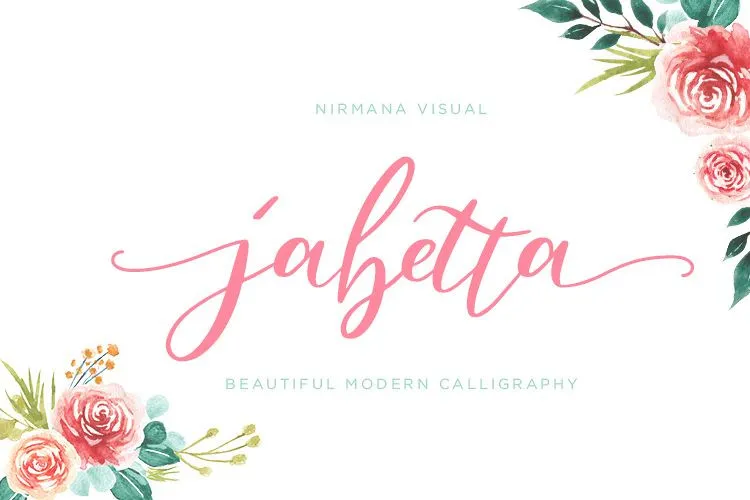
Jabetta Script Font – Download Grátis
A Jabetta Script Font é uma elegante tipografia moderna inspirada na calligrafia. Este tipo de texto possui características únicas que a tornam perfeita para diferentes necessidades de design, especialmente ideal para criações de marca e projetos especiais. Construída cuidadosamente a partir do real traçado manual, ela transmite uma sensação de naturalidade e casualidade, com um estilo fluido e encantador. Integrada em convites de casamento, presentes, marcas da marca ou logotipos até mesmo para promover sua própria empresa pessoal, a Jabetta Script é uma fonte perfeita que se combina bem com estilos de fontes diferentes. Ela também oferece um grande número de adições, como ligaturas e swashes sobressaientes na linha de baixo, tornando seus projetos mais atraentes e chamativas. Esta fonte não apenas é bonita para o olho, mas também fácil de usar, tornando-a uma escolha ótima para qualquer designer que esteja procurando um estilo elegante e único. Seja você criando convites de casamento com um toque romântico ou personalizando os marcas do seu negócio pessoal, a Jabetta Script é uma fonte ideal para sua necessidade de design.